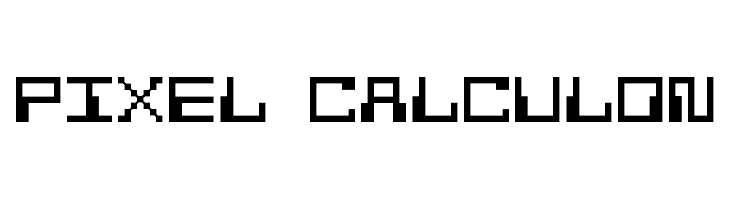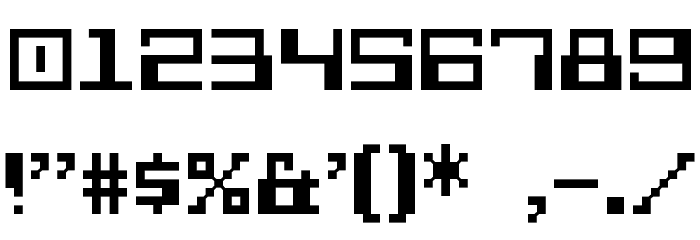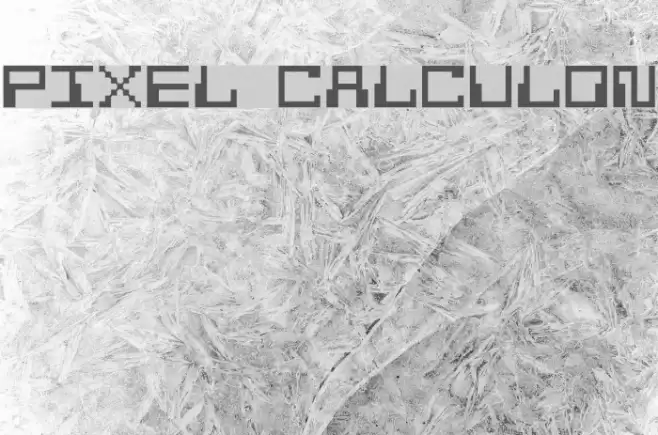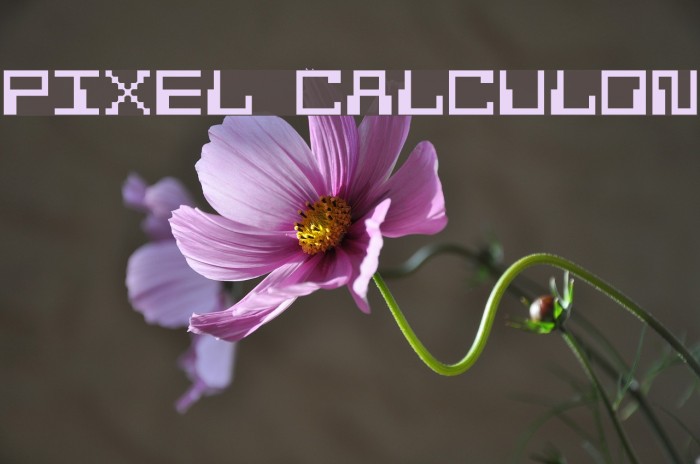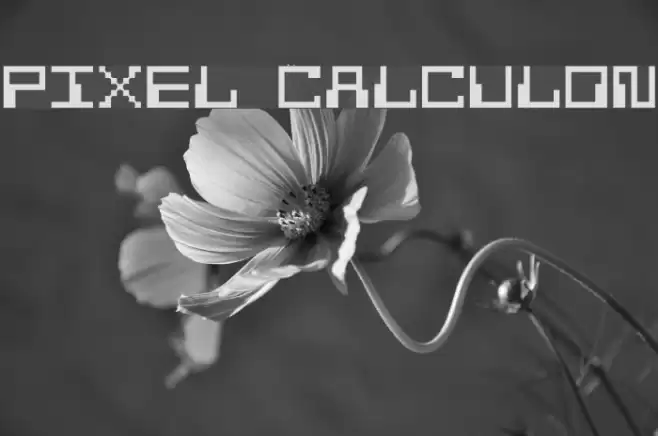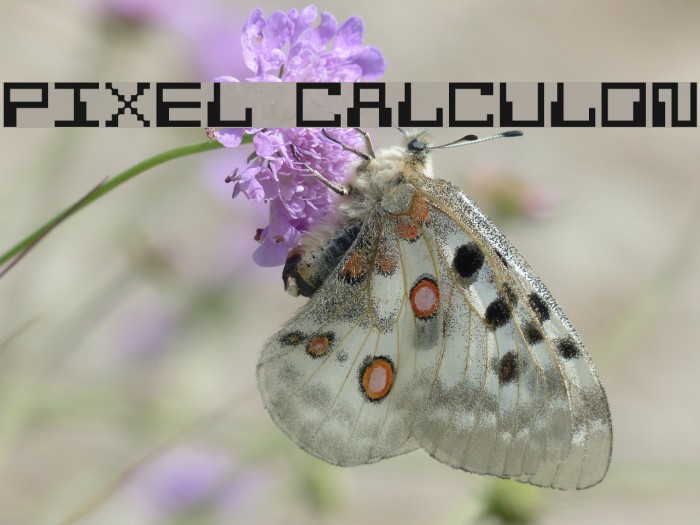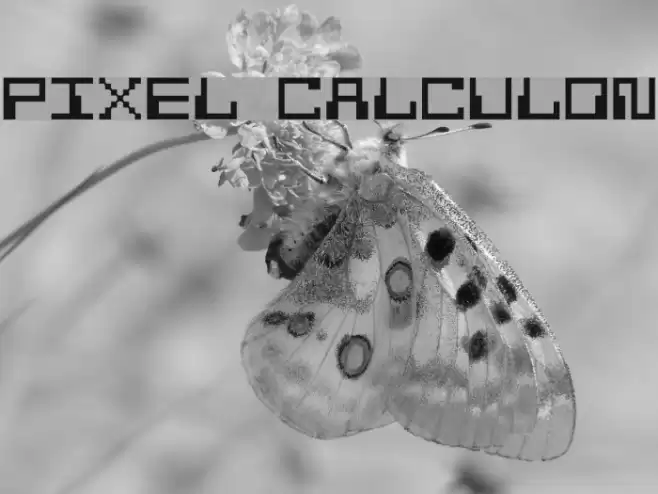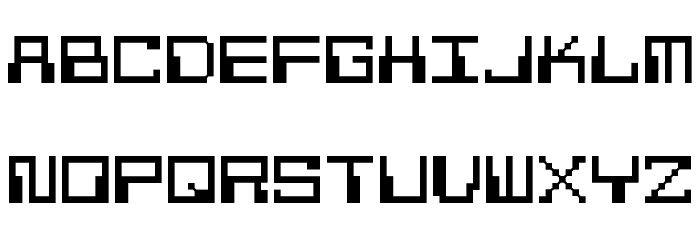
Pixel Calculon Font
✎ Futuristic
| Kategorien | Futuristic |
| Gesamtstil | Vintage |
| Anwendungsfall | Logos, Headlines, Digital Art |
| Vorgeschlagene Projekte | Ideal for retro-themed designs, video game graphics, digital art projects, and tech-related branding. |